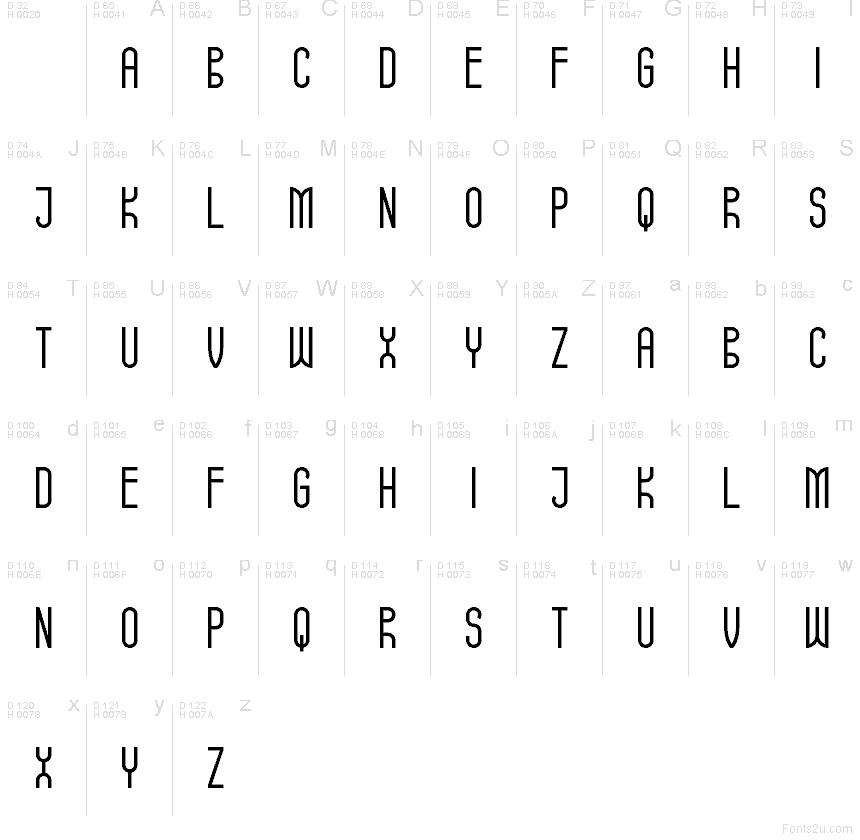
Broadcaster Retro od Vladimira Nikolica to darmowy, retro font typu display o eleganckim rysie ery radiowej. Wielkie litery są wysokie, gładkie i zwarte, łącząc zaokrąglone zewnętrzne łuki z ostrymi wewnętrznymi cięciami, co nadaje napisom płynny, plakatowy rytm.
Font naturalnie wpisuje się w branding kawiarni, okładek płyt, plakatów eventowych, nagłówków czasopism i plansz tytułowych, wszędzie tam, gdzie kilka słów wymaga nostalgicznego sznytu ery maszynowej. Jako darmowy font, sprawdza się również w monogramach i krótkich nazwach na opakowaniach, ponieważ litery układają się w zwarty, ciągły strumień, który bardziej oddziałuje graficznie, niż czytelniczo.